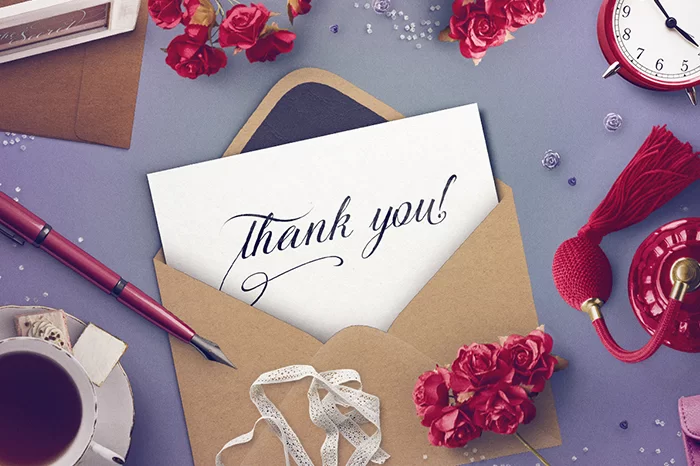
TheSecret là kiểu chữ viết tay với hơn 50 nét gạch ngang cuối. Nó là kiểu chữ mở! Nó thông minh và hoạt động được trong Photoshop mà không cần mở bảng glyph! Bạn có thể sử dụng nó cho nhiều mục đích khác nhau: logo, thiệp cưới, tiêu đề, chữ ký, áo thun, tiêu đề thư, biển báo, nhãn, áp phích, v.v.
Nhà thiết kế: Dmitrii Mikitenko
Nhà phát hành: BlessedPrint
Năm: 2015
Kiểu: Regular